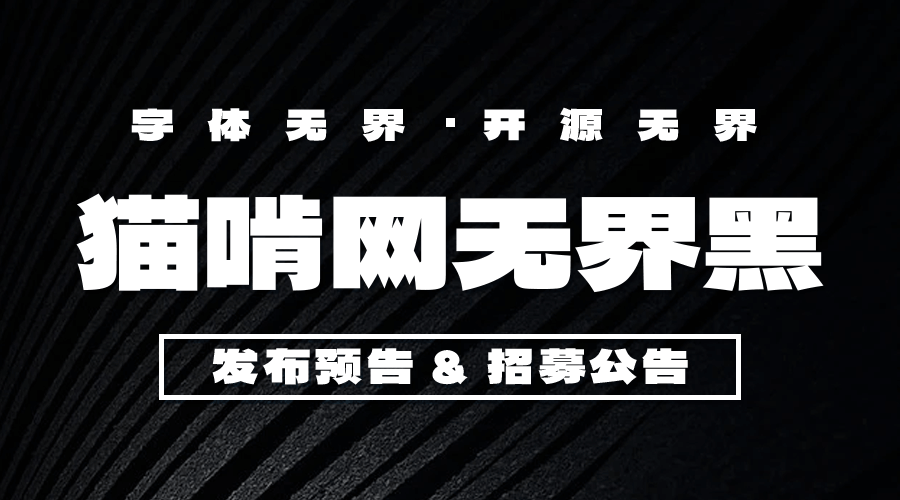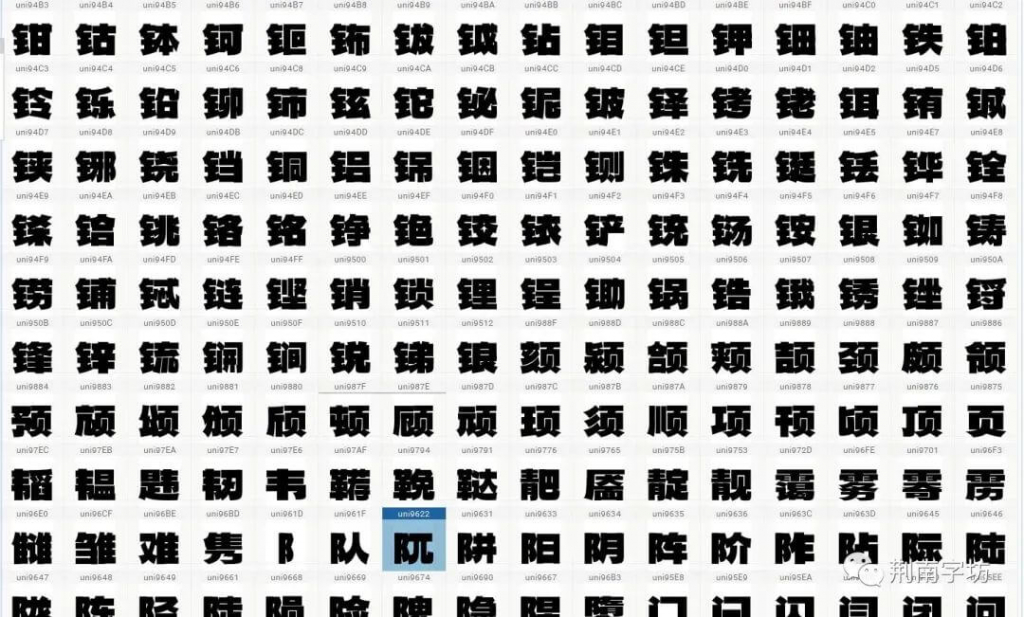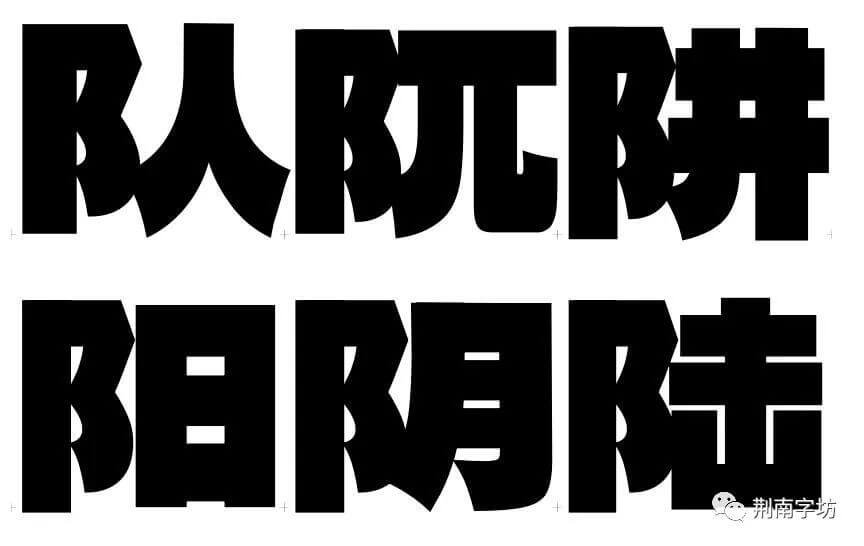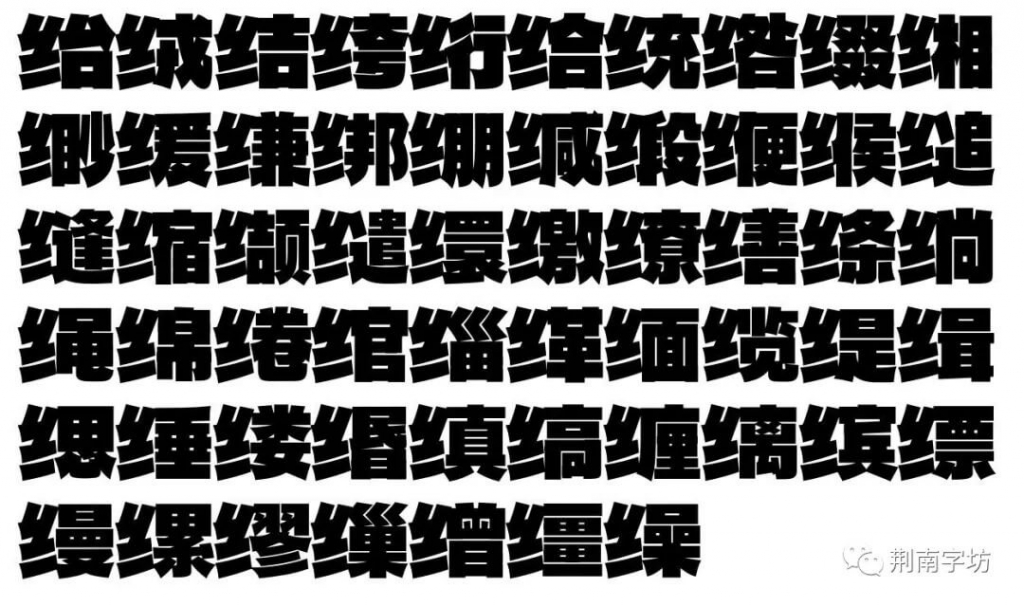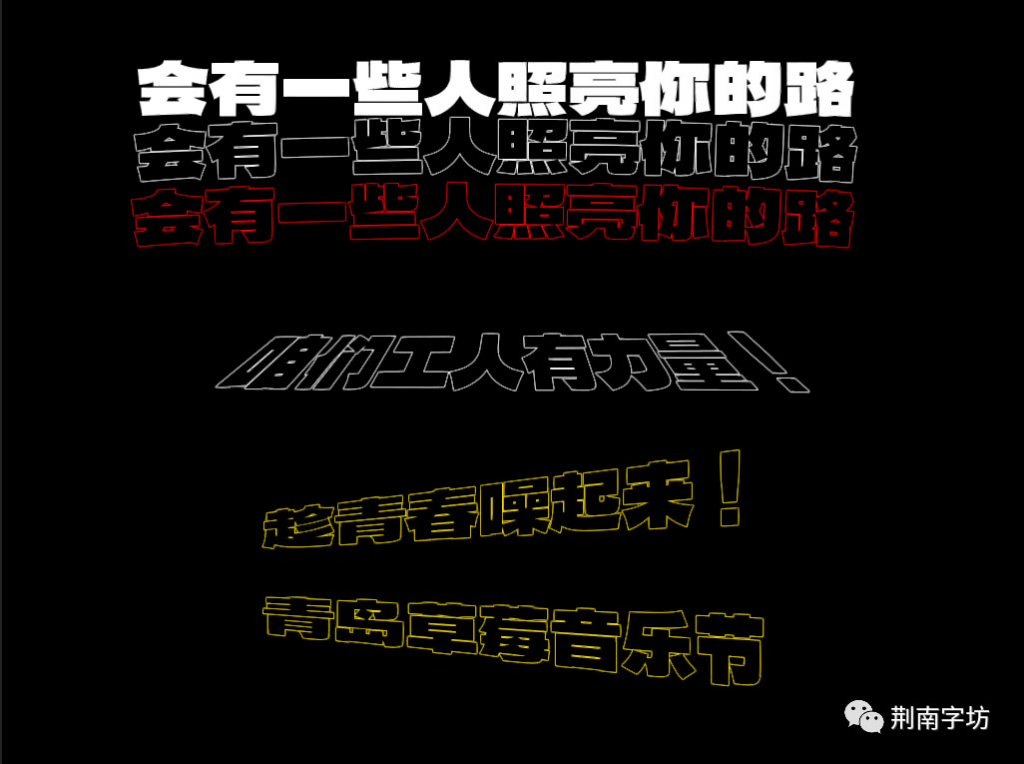
之前,猫啃君在猫啃网上转载了一款日本作者aratakana制作的开源字体德拉黑体(日文名:デラゴシック,英文名:DelaGothic)。德拉黑体是一款扁平的,笔画非常粗的标题字体,其稳定性和强度使其非常适合在海报和包装上使用。德拉黑体字符框架水平放置,具有非常稳重的特性。
猫啃君觉得德拉黑体是一款十分适合用于海报设计的标题字体,奈何简体字数不多,对于我们中国大陆的小伙伴来说实在是太可惜了。于是在@荆南字坊、@夜煞之乐、@笑频书、@落霞孤鹜、@时光羊、@hulenkius、@ᴍᴀᴏʏᴠ、@派对大魔王、@刘鹏、@ZERO_子、@觉醒年代、@Siphercase、@汤三等等(参与的朋友名单未能一一列举,如有遗漏敬请原谅)的大侠们的支持下开始了德拉黑体的补简之旅。
字体暂时命名为“猫啃网无界黑”,意为字体无界,开源无界。目前已经将原字体GB2312标准内的汉字字形更改为符合国标的字型,并且完成了缺字补字工作的将近一半。
如果没有新的朋友加入,那么这款字体预计在11月发布。
这款字体很有价值!活动海报、场景设计都用得到。粗壮但灵动,视觉效果很好。支持楼主工作。